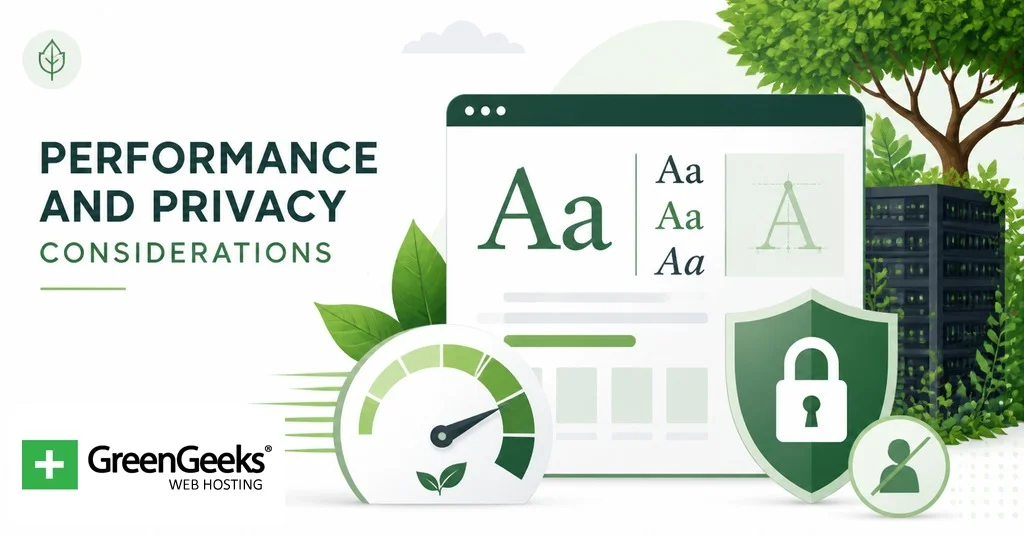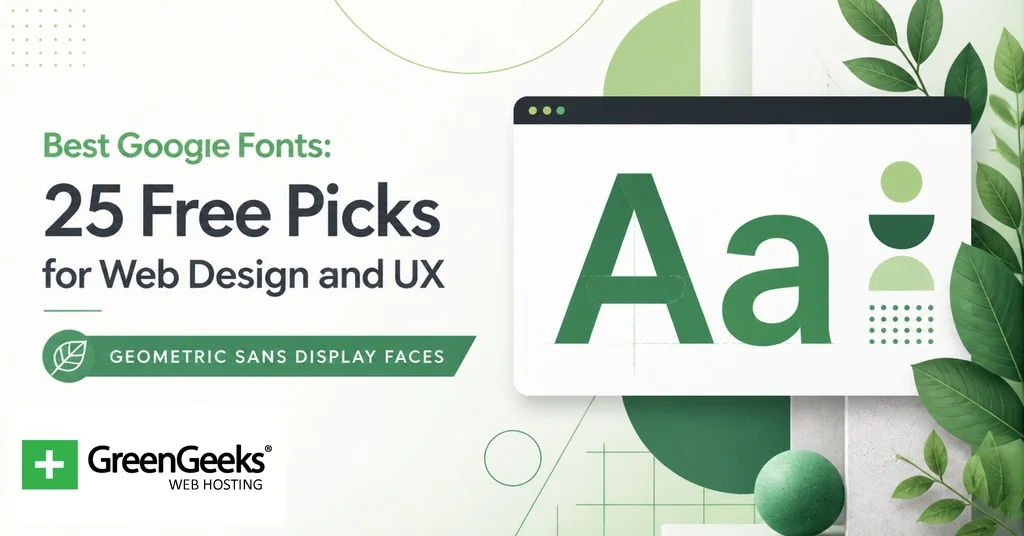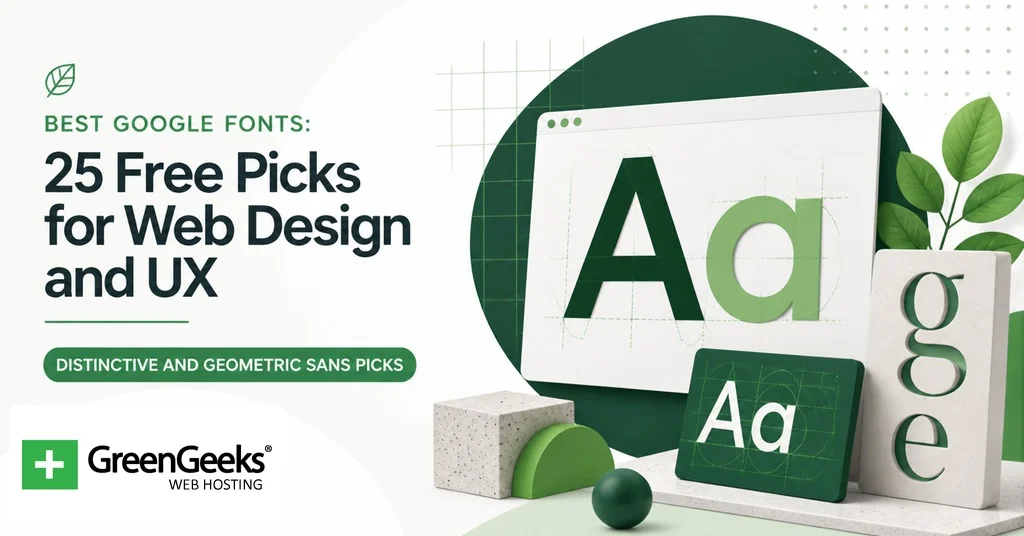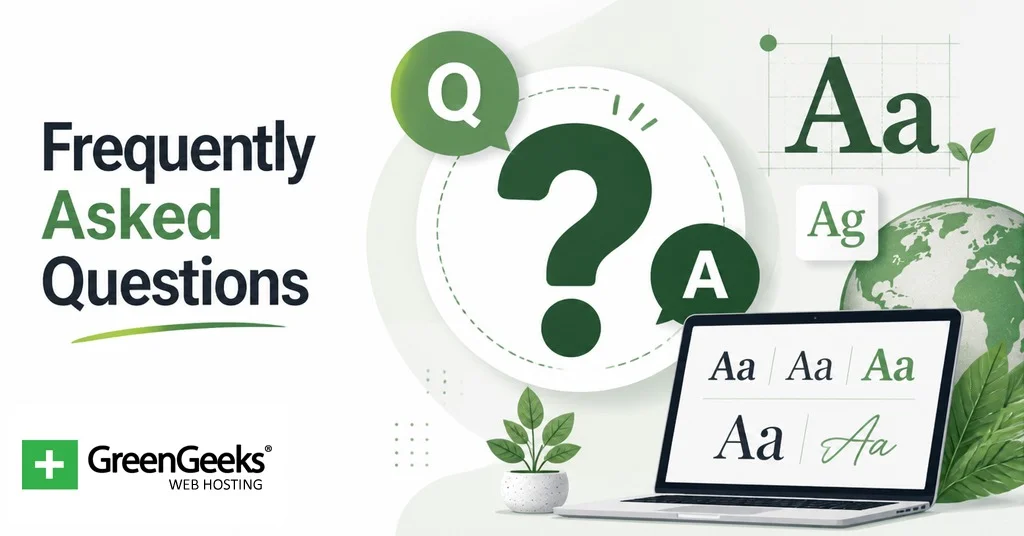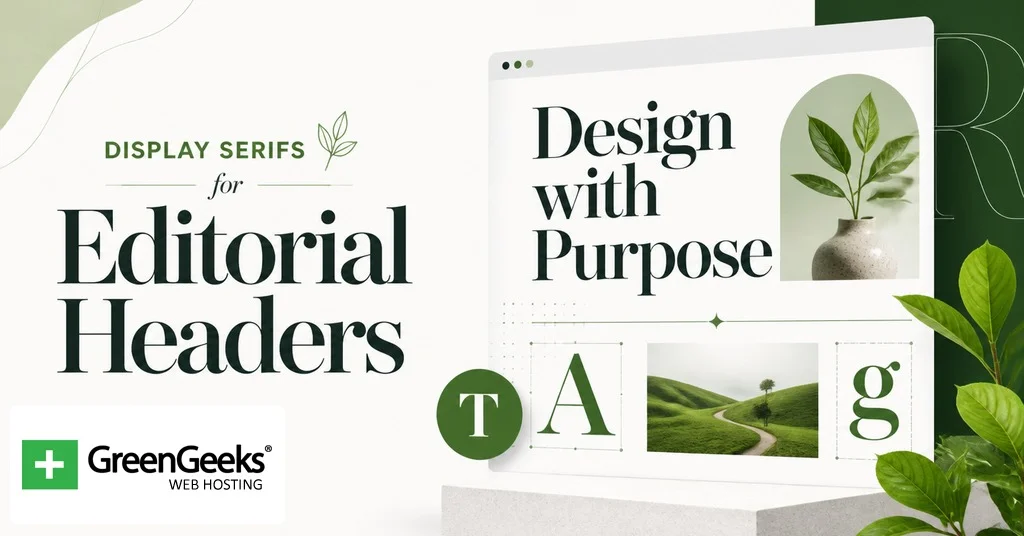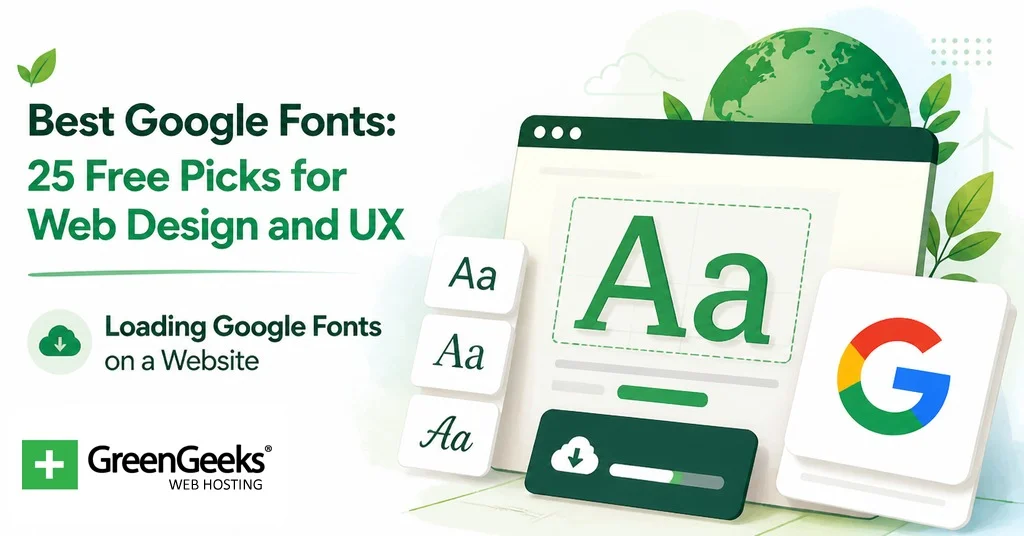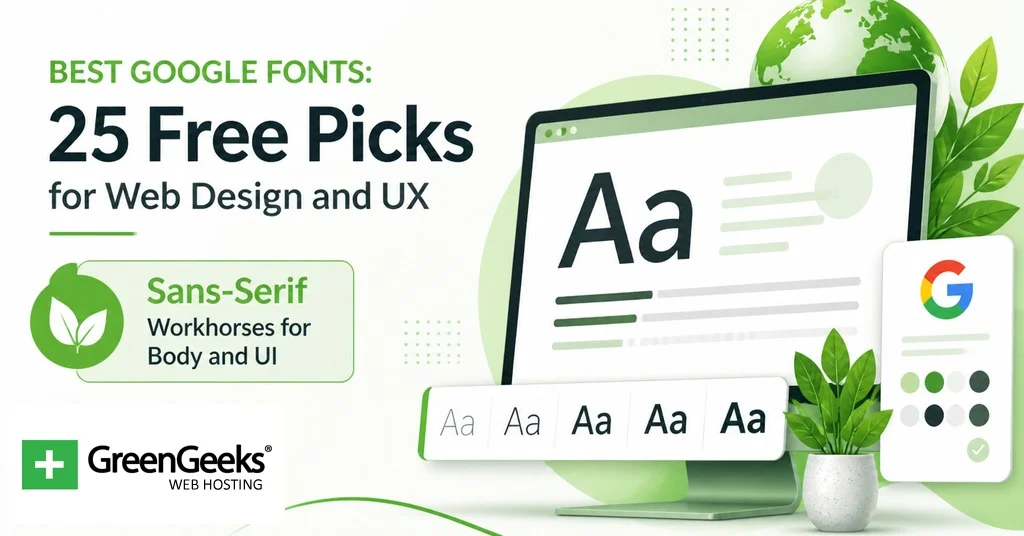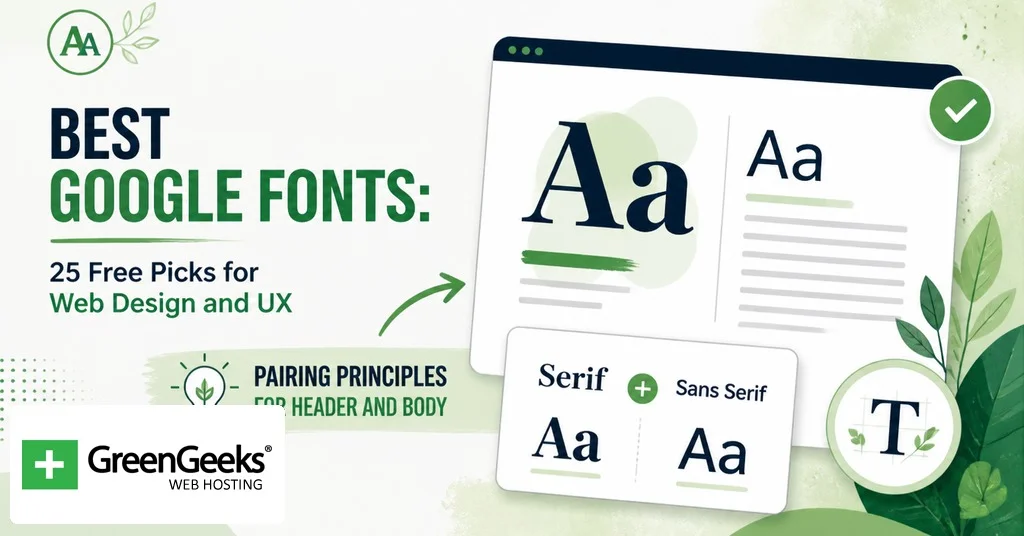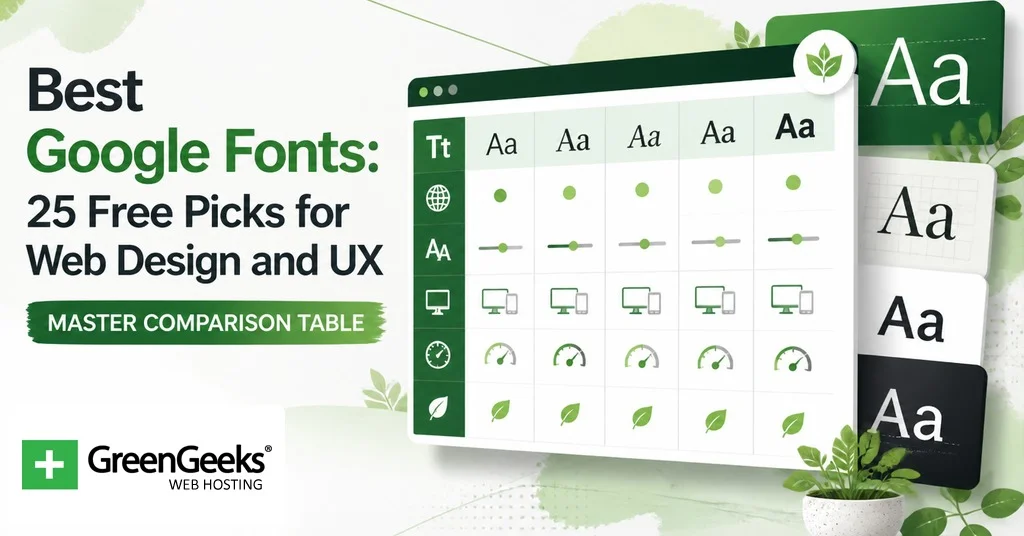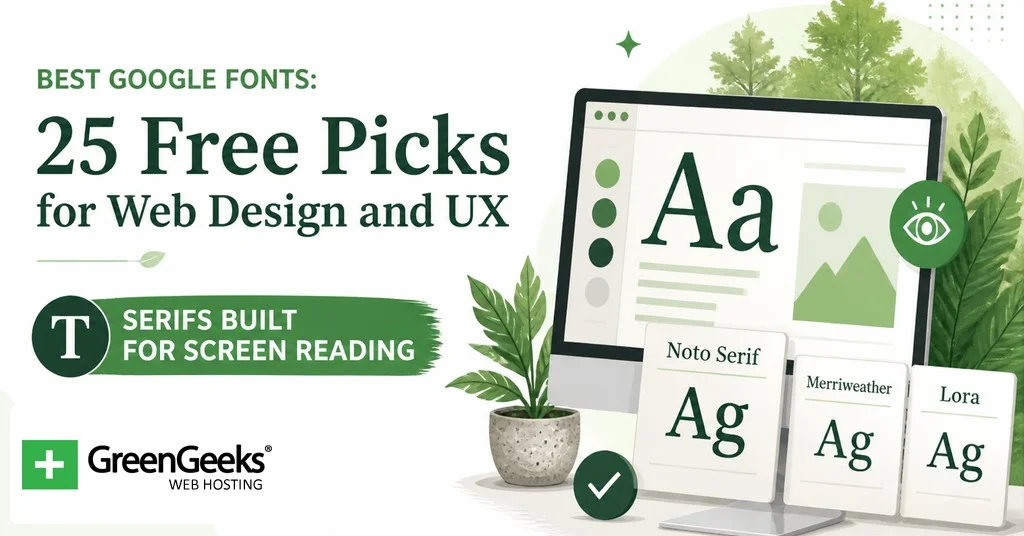
Inter, Roboto и Open Sans — самые используемые шрифты Google Fonts в открытом вебе, потому что они созданы для экранов, доступны во многих начертаниях и имеют открытую лицензию, разрешающую коммерческое встраивание. Приведённые ниже 25 вариантов расширяют это ядро в область шрифтов с засечками, брусковых, узких, моноширинных и адаптированных для доступности, чтобы дизайнер мог построить целый сайт — от геройских заголовков до сносок и примеров кода — не покидая каталога Google Fonts. Критериями являются данные об использовании, количество начертаний, оптический размер, языковое покрытие и то, как каждый шрифт выглядит в размерах для основного текста на базовой линии 16px.
Библиотека Google Fonts насчитывала 1 826 семейств в мае 2025 года и суммарно набрала более 50 триллионов просмотров на 50 миллионах веб-сайтов. Roboto лидирует по совокупным просмотрам — около 28 триллионов, а Inter за год, закончившийся в мае 2025 года, набрал 414 миллиардов просмотров, показав рост 57% год к году. Эти две цифры объясняют, почему большинство современных интерфейсов кажутся знакомыми. Приведённый ниже список рассматривает их как основу и добавляет ещё 23 шрифта, которые решают разные задачи: редакционные заголовки, доступность, код, брендинг.
Критерии отбора 25 шрифтов
Пять факторов сформировали шорт-лист. Первый — реальное использование. Шрифты, набравшие не менее миллиарда просмотров в год на Google Fonts, продвигались вверх, поскольку широкое распространение обычно коррелирует с качеством отображения в разных браузерах и операционных системах. Второй — количество начертаний. Шрифты, поставляемые с пятью и более начертаниями, дают дизайнерам пространство для иерархии без необходимости подключать второе семейство. Третий — оптический размер или экранная настройка. Inter, Roboto, Lexend и Atkinson Hyperlegible были созданы с явной целью отображения на экране с попиксельным рендерингом, что проявляется в том, как они выглядят при малом размере основного текста.
Четвёртым фактором стало языковое покрытие. Одной латиницы достаточно для большинства англоязычных сайтов, но расширенная латиница, кириллица и греческий важны для международного UX. PT Serif, Open Sans, EB Garamond и Atkinson Hyperlegible имеют хорошую поддержку нескольких письменностей. Пятым фактором стал размер файла после поднабора. Переменный шрифт в Google Fonts обычно занимает от 20 до 30 КБ после применения латинского поднабора, по сравнению с 400–800 КБ для эквивалентного набора статических файлов. Эта разница важна для показателей Largest Contentful Paint на мобильных устройствах.
Сводная сравнительная таблица
| Шрифт | Классификация | Начертания | Переменная ось | Лучше всего для |
| Inter | Нео-гротескный без засечек | 9 | Начертание, оптический размер | Основной текст, UI |
| Roboto | Нео-гротескный без засечек | 6 | Начертание, ширина (Flex) | Основной текст, UI |
| Open Sans | Гуманистический без засечек | 7 | Начертание | Основной текст, блог |
| Lato | Гуманистический без засечек | 9 | Только статические | Основной текст, бренд |
| Source Sans 3 | Гуманистический без засечек | 8 | Начертание | Основной текст, документация |
| Work Sans | Без засечек, адаптированный для экранов | 9 | Начертание | Основной текст, UI |
| Nunito | Закруглённый без засечек | 7 | Начертание | Дружественный интерфейс |
| DM Sans | Геометрический без засечек | 5 | Начертание, оптический размер | Мелкий текст |
| Montserrat | Геометрический без засечек | 9 | Начертание | Заголовки, бренд |
| Poppins | Геометрический без засечек | 9 | Только статические | Заголовки, бренд |
| Plus Jakarta Sans | Геометрический без засечек | 6 | Начертание | UI для SaaS |
| Manrope | Геометрический без засечек | 7 | Начертание | UI для SaaS |
| Bebas Neue | Узкий акцидентный | 1 | Только статические | Плакаты, геройский |
| Oswald | Узкий без засечек | 6 | Начертание | Новостные заголовки |
| Archivo | Без засечек, готический | 9 | Начертание, ширина | Редакционные |
| Raleway | Акцидентный без засечек | 9 | Начертание | Бренд, геройский |
| Space Grotesk | Пропорциональный без засечек | 5 | Начертание | Технологический бренд |
| Merriweather | Брусковый с засечками для основного текста | 4 | Только статические | Длинный основной текст |
| Lora | Каллиграфический с засечками | 4 | Начертание | Редакционный основной текст |
| PT Serif | Переходный с засечками | 2 | Только статические | Многоязычный основной текст |
| Playfair Display | Переходный акцидентный с засечками | 6 | Начертание | Редакционный заголовок |
| DM Serif Display | Высококонтрастный с засечками | 1 | Только статические | Геройский заголовок |
| EB Garamond | Старостильный с засечками | 5 | Начертание | Чтение длинных текстов |
| Roboto Slab | Брусковый с засечками | 9 | Начертание | Заголовки с привязкой к основному тексту |
| JetBrains Mono | Моноширинный | 8 | Начертание | Блоки кода |
Рабочие лошадки без засечек для основного текста и интерфейсов
Эти восемь шрифтов справляются с текстом абзацев, надписями навигации, полями форм и большинством интерфейсного текста. Их объединяют три качества, делающие их безопасным выбором по умолчанию: щедрая высота строчных, равномерный интервал и хинтинг для экранов с низким разрешением.
1. Inter
Созданный Расмусом Андерссоном и выпущенный в 2017 году, Inter — это нео-гротескный шрифт без засечек, оптимизированный для текста пользовательского интерфейса малых размеров. Переменный файл содержит как ось начертания (от 100 до 900), так и ось оптического размера с тремя мастер-дизайнами для 100, 400 и 900. Inter используется по умолчанию в нескольких крупных дизайн-системах и набрал 414 миллиардов просмотров в Google Fonts за год, закончившийся в мае 2025 года.
Чисто сочетается с самим собой. Один файл Inter с переменным начертанием покрывает заголовки, основной текст и UI без второго семейства.
2. Roboto
Кристиан Робертсон разработал Roboto для Android 4.0 в 2011 году. Он поставляется в начертаниях Thin, Light, Regular, Medium, Bold и Black, а также в наклонных версиях, а в 2022 году получил переменную версию Roboto Flex. Roboto имеет наибольшее количество просмотров за всё время в Google Fonts — около 28 триллионов. Его двойственный характер — геометрический скелет с гуманистическими кривыми — придаёт ему нейтральность, которая адаптируется к большинству продуктовых контекстов.
Пример сочетания: Roboto для основного текста, Roboto Slab для H1.
3. Open Sans
Open Sans — это гуманистический шрифт без засечек, созданный Стивом Мэттесоном по заказу Google в 2011 году. Набор символов охватывает 897 глифов для латиницы, греческого и кириллицы. Он имеет открытые формы букв и слегка вертикальный наклон, что обеспечивает читаемость длинных абзацев на маленьких экранах.
Примечание дизайнера: Мэттесон основал семейство на своём более раннем Droid Sans, созданном для Android в 2008 году.
4. Lato
Lato — это гуманистический шрифт без засечек, разработанный польским дизайнером шрифтов Лукашем Дзедичем и выпущенный в 2010 году. Он поставляется в 9 начертаниях с соответствующими курсивами. Шрифт имеет полузакруглённые формы букв, которые воспринимаются как тёплые, не теряя структурной строгости.
Обычное применение: корпоративные сайты и образовательные платформы, которым нужна более дружелюбная альтернатива Roboto.
5. Source Sans 3
Первый открытый шрифт Adobe, созданный Полом Хантом и выпущенный в 2012 году под названием Source Sans Pro. Source Sans 3 — это переименованный преемник с открытым исходным кодом. Шрифт поставляется в 8 начертаниях от ExtraLight до Black с соответствующими курсивами. Формы букв чистые и слегка узкие, поэтому текст набирается компактно, не кажется сжатым.
Используйте его там, где важна плотность документации, например в справках API или документации продуктов.
6. Work Sans
Адаптированный для экрана шрифт без засечек от Вэй Хуанга. Средние начертания (от 400 до 600) разработаны для размеров от примерно 14px до 48px. Более лёгкие и более жирные начертания имеют более декоративные начертания, поэтому дизайнеры могут переходить к акцидентному использованию, не меняя семейство.
7. Nunito
Вернон Адамс разработал Nunito как шрифт без засечек с закруглёнными концами. Закруглённые углы придают шрифту более мягкое ощущение по сравнению с Inter или Roboto. Nunito Sans, версия без закруглений, находится рядом с ним в каталоге Google Fonts для случаев, когда мягкие окончания кажутся слишком игривыми.
Сочетается с Lora для дружелюбной редакционной блог-системы.
8. DM Sans
DM Sans — это малоконтрастный геометрический шрифт без засечек от Colophon Foundry и Indian Type Foundry. Шрифт предназначен для малых размеров текста и поставляется с переменным файлом, имеющим ось начертания и ось оптического размера. Более плотный интервал хорошо читается в плотных панелях интерфейса и дашбордах.
Геометрические акцидентные шрифты без засечек
Эта группа склоняется к брендингу и заголовкам. Геометрия создаёт уверенное, современное впечатление. Использование для основного текста возможно, но открытые внутренние просветы могут казаться разреженными в длинных отрывках.
9. Montserrat
Хульета Улановски создала Montserrat в 2011 году, вдохновившись старыми плакатами и вывесками в районе Монтсеррат в Буэнос-Айресе. Семейство поставляется в 9 начертаниях. Геометрическая конструкция делает его частым выбором для геройских заголовков, фирменных знаков и слайдов презентаций.
Заметка из данных об использовании: Montserrat входит в тройку лучших шрифтов Google Fonts последние пять лет подряд.
10. Poppins
Геометрический гротеск от Indian Type Foundry, с указанием авторства Джонни Пинхорна и Нинада Кале. Poppins охватывает латиницу и деванагари, что редко встречается среди шрифтов Google Fonts. Поставляется в 9 начертаниях от Thin до Black. Буквенные формы почти монолинейны, что придает чистый, маркетинговый вид.
Пример сочетания: Poppins для заголовков, PT Serif для основного текста.
11. Plus Jakarta Sans
Спроектирован Гумпитой Рахаю из Tokotype. Выпущенный как SaaS-ориентированный геометрический гротеск, этот семейство набрало популярность в контексте стартапов и интерфейсов продуктов, где Inter кажется слишком избитым. Шесть начертаний с соответствующими курсивами.
12. Manrope
Manrope от Михаила Шаранды находится между геометрическим и гротескным. По духу ближе к коммерческим гарнитурам, таким как Circular, имеет слегка закрытые полуапроши, которые не позволяют геометрическим буквам выглядеть слишком открытыми при крупных размерах. Семь начертаний.
Узкие и жирные акцидентные гротески
Для плакатов, геройских секций и коротких блоков с сильным визуальным воздействием. Ни один из этих трех шрифтов не предназначен для набора абзацев.
13. Bebas Neue
Спроектированный Рёичи Цунекавой и добавленный в Google Fonts в 2018 году, Bebas Neue содержит только заглавные буквы и является узким. Версия в Google Fonts поставляется в единственном начертании. Bebas Neue Pro, продаваемая отдельно, добавляет строчные, но в большинстве редакторских применений Bebas Neue используется как полностью заглавный плакатный шрифт.
14. Oswald
Вернон Адамс переработал стиль Alternate Gothic для создания Oswald. Семейство поставляется в 6 начертаниях с полным набором строчных, что отличает его от Bebas Neue. Oswald подходит для газетных заголовков, шапок спортивных сайтов и любых макетов, требующих вертикального сжатия.
15. Archivo
Archivo вдохновлен американским готическим шрифтом XIX века. Релиз в Google Fonts поставляется как вариативный шрифт с осями ширины и начертания. Узкие начертания выглядят редакционно; обычные — как утилитарный гротеск для форм и плотных таблиц.
Выразительные и геометрические гротески
Два шрифта, решающие более узкие задачи, чем рабочие лошадки, но часто встречающиеся в современных бренд-системах.
16. Raleway
Изначально нарисован Мэттом Макинерни в 2010 году как единственное тонкое акцидентное начертание. Позже Пабло Импаллари и Родриго Фуэнсалида расширили семейство до 9 начертаний с курсивами. Raleway лучше всего смотрится при крупных размерах; тонкие и сверхлегкие начертания имеют фирменные лигатуры и слегка ар-дековую геометрию.
17. Space Grotesk
Флориан Карстен выпустил Space Grotesk в 2018 году как пропорциональный гротеск, производный от моноширинного Space Mono (2016) от Colophon Foundry. Семейство сохраняет своеобразные кривые и угловые срезы моноширинного оригинала, но оптимизирует межбуквенные расстояния для размеров, не связанных с отображением. Пять начертаний, без курсивов. Выглядит технологично, не переходя в научно-фантастический вид полностью геометрических шрифтов.
Антиквы для чтения с экрана
Три антиквы, которые успешно перешли из печати на экран. Каждая обладает большой высотой строчных знаков и слегка открытыми буквенными формами, которые хорошо смотрятся на экранах телефонов.
18. Merriweather
Sorkin Type разработал Merriweather как антикву для чтения с экрана. Шрифт имеет большую высоту строчных, слегка уплотненные формы и очень открытые апертуры. Это одна из самых часто цитируемых антикв для текста в блогах и публикациях. Четыре начертания от Light до Black.
19. Lora
Современная антиква с каллиграфическими корнями от Cyreal. По последним данным, Lora используется на более чем 1,5 миллионах сайтов. Она обладает достаточной теплотой для редакционного вида, не теряя регулярности, необходимой для абзацев. Четыре начертания с соответствующими курсивами.
20. PT Serif
PT Serif от ParaType поставляется с наборами латиницы, центральноевропейских языков и кириллицы. Семейство метрически совместимо с PT Sans, то есть оба семейства имеют одинаковую высоту строк и пропорции, поэтому они легко заменяют друг друга в системе. Два начертания с курсивами плюс два стиля для подписей.
Акцидентные антиквы для редакционных заголовков
Эти шрифты раскрываются при размере 32px и выше. Ни один из них не подходит для основного текста.
21. Playfair Display
Переходная антиква от Клауса Эггерса Соренсена. Дизайн отсылает к европейским шрифтам XVIII века и поставляется в 6 начертаниях. Высокий контраст штрихов и длинные верхние выносные элементы придают ему редакционный вид заголовка модного журнала. Обычно Playfair Display сочетают с чистым гуманистическим гротеском для основного текста.
22. DM Serif Display
Высококонтрастная переходная антиква, созданная для плакатов и геройских секций. Закругления деликатны, контраст штрихов сильный, а формы букв сохраняются только при больших размерах. В релизе Google Fonts одно начертание плюс курсив. Используйте при 40px или больше.
23. EB Garamond
Георг Майр-Даффнер нарисовал EB Garamond как бесплатное научное возрождение шрифтов Клода Гарамона XVI века. Пять начертаний с соответствующими курсивами. Семейство поддерживает латиницу, греческий и кириллицу. Дизайнеры обращаются к нему, когда контекст длинного чтения требует литературного регистра.
Брусковые и моноширинные шрифты
Два шрифта, дополняющих систему: брусковый для промежутка между гротеском и антиквой, и моноширинный для примеров кода.
24. Roboto Slab
Брусковая версия Roboto, выпущенная в марте 2013 года как шрифт по умолчанию для Google Keep. Семейство поставляется в 9 начертаниях от Thin до Black. Основное применение — компаньон для заголовков к основному тексту Roboto, где совпадающий скелет обеспечивает тесную визуальную связь.
25. JetBrains Mono
JetBrains выпустила JetBrains Mono в 2020 году под лицензией SIL Open Font License. Шрифт был нарисован для редакторов кода с максимальной высотой строчных для четкости при размерах 12–14px. Восемь начертаний с курсивами. Встроенный в любой документационный сайт или продукт, ориентированный на разработчиков, он придает блокам кода продуманный, инженерный вид.
Принципы сочетания заголовков и основного текста
Системы из двух шрифтов обычно побеждают. В большинстве продакшн-сайтов используется один акцидентный шрифт для H1 и H2 и один рабочий для основного текста, навигации и интерфейса. Иногда добавляют третий для кода или цифр, но после трех страница начинает выглядеть несогласованно.
Сильные сочетания работают на контрасте. Сочетайте высококонтрастную антикву с низкоконтрастным гротеском. Сочетайте геометрический гротеск с гуманистической антиквой. Сочетайте узкий акцидентный шрифт с широким рабочим. Сочетания в одном настроении обычно проваливаются, потому что страница теряет иерархию. Три надежных сочетания из списка выше: Playfair Display с Source Sans 3, Montserrat с Merriweather и Inter с самим собой в разных начертаниях.
Совпадение высоты строчных — второе правило. Если у шрифта для основного текста большая высота строчных, а у заголовочного — маленькая, то при одинаковом размере в пикселях основной текст будет выглядеть крупнее заголовков. PT Serif и PT Sans были спроектированы вместе специально для решения этой проблемы. Inter и Roboto Slab обладают достаточно схожей пропорциональной ДНК, чтобы вести себя аналогично. При сочетании шрифтов разных найденрий ставьте оба рядом в нужных размерах и проверяйте оптический баланс перед запуском.
Третье правило, которое стоит соблюдать, — ограничение начертаний. Используйте не более трех начертаний на шрифт на одной странице. Типичная настройка: Regular для основного текста, Medium для акцентов и Bold для заголовков. Добавление дополнительных начертаний не повышает ясность, а размывает иерархию.
Загрузка Google Fonts на сайте
Есть два способа загрузить шрифт Google с CDN Google, плюс третий — самостоятельный хостинг тех же файлов. У каждого есть свои компромиссы по производительности, конфиденциальности и кэшированию. Шаги по реализации ниже охватывают все три.
Выберите шрифт и начертания на fonts.google.com и скопируйте сгенерированный тег link.
Вставьте тег link в head HTML перед основным файлом стилей.
Укажите шрифт в CSS с помощью объявления font-family.
Добавьте font-display: swap в блок @font-face (или положитесь на значение по умолчанию Google, которое уже включает swap).
Для самостоятельного хостинга скачайте файлы шрифтов через кнопку загрузки Google Fonts, поместите их в папку /fonts и вручную напишите блок @font-face.
Добавьте тег link с rel=preload для наиболее используемого файла шрифта, чтобы устранить смещение макета при первой отрисовке.
Подход с тегом link выглядит так:
<link rel="preconnect" href="https://fonts.googleapis.com"> <link rel="preconnect" href="https://fonts.gstatic.com" crossorigin> <link href="https://fonts.googleapis.com/css2?family=Inter:wght@400;600;700&display=swap" rel="stylesheet">
Альтернатива CSS @import загружает те же файлы, но блокирует рендеринг до разрешения импорта:
@import url('https://fonts.googleapis.com/css2?family=Inter:wght@400;600;700&display=swap'); body { font-family: 'Inter', system-ui, sans-serif; }
Самостоятельно размещенный блок выглядит так и полностью исключает сторонний запрос:
@font-face { font-family: 'Inter'; src: url('/fonts/inter-variable.woff2') format('woff2-variations'); font-weight: 100 900; font-display: swap; }
Сочетайте самостоятельно размещенный блок с тегом preload в заголовке документа для соответствующего файла, и страница будет отрисована при первой отрисовке с веб-шрифтом без мигания запасного варианта.
Вопросы производительности и конфиденциальности
Переменный шрифт заменяет от 4 до 9 статических файлов одним. После латинской подрезки типичный переменный шрифт из Google Fonts весит от 20 до 30 КБ, тогда как эквивалентный набор статических файлов — от 400 до 800 КБ. Такое сокращение полезной нагрузки напрямую влияет на Largest Contentful Paint в мобильных сетях. Для сайта, которому нужна только латиница, применение текстового URL-параметра в запросе к Google Fonts или запуск pyftsubset на самостоятельно размещённом файле уменьшает размер файла ещё на 70–90 процентов.
Свойство CSS font-display управляет тем, что происходит, пока файл загружается. Установка font-display: swap немедленно отображает запасной шрифт и заменяет его веб-шрифтом, когда тот готов, что обменивает короткую вспышку нестилизованного текста (FOUT) на более быстрый First Contentful Paint. Установка font-display: optional даёт браузеру около 100 миллисекунд на загрузку шрифта; если он не успевает, запасной шрифт фиксируется на всю загрузку страницы. Комбинация предзагрузки, optional и самостоятельно размещённого файла устраняет как FOIT (вспышку невидимого текста), так и FOUT на большинстве кэшированных посещений.
Проблема конфиденциальности специфична для CDN Google. В январе 2022 года Мюнхенский земельный суд постановил, что загрузка шрифтов Google с fonts.googleapis.com без согласия передаёт IP-адрес пользователя в США и нарушает GDPR. Истцу была присуждена компенсация в размере 100 евро, и суд указал на более высокие штрафы за повторные нарушения. Множество судов ЕС последовали этому прецеденту. Самостоятельное размещение файлов шрифтов решает проблему, поскольку при загрузке страницы не выполняется внешний запрос. Лицензия Open Font License явно разрешает такое распространение. Для сайта со значительным европейским трафиком самостоятельное размещение является более безопасным выбором по умолчанию в 2026 году.
Практическая настройка объединяет три шага: загрузите переменный шрифт из Google Fonts, выполните латинскую подрезку с помощью pyftsubset и разместите файл на том же домене, что и сайт, с длинным заголовком Cache-Control и тегом предзагрузки. Такая конфигурация обеспечивает полезную нагрузку менее 30 КБ, отсутствие сторонних запросов и отсутствие FOIT на кэшированных посещениях.
Часто задаваемые вопросы
Какой шрифт Google лучше всего подходит для веб-сайтов?
Inter, Roboto и Open Sans возглавляют списки использования и рекомендаций для общих веб-задач. Они были разработаны для экранов, поставляются во многих начертаниях и хорошо читаются в размерах основного текста от 16 до 18 пикселей. Inter показывает самый сильный текущий рост в Google Fonts, в то время как Roboto занимает наибольшую совокупную долю — примерно 28 триллионов просмотров за всё время.
Какой шрифт Google самый читаемый?
Inter и Open Sans чаще всего упоминаются как наиболее читаемые для основного текста благодаря высокой высоте строчных букв, открытым формам и равномерным интервалам. Для читателей с ослабленным зрением или трудностями при чтении Atkinson Hyperlegible (выпущен Институтом Брайля в 2021 году) и Lexend (разработан для улучшения навыков чтения) являются самыми сильными вариантами с точки зрения доступности в каталоге Google Fonts.
Можно ли использовать Google Fonts в 2026 году?
В целом да, но загрузка шрифтов с CDN Google без предварительного согласия была признана нарушением GDPR Мюнхенским земельным судом и рядом последующих дел. Самостоятельное размещение тех же файлов шрифтов устраняет этот риск, сохраняя преимущества лицензии Open Font License, и обычно улучшает производительность за счёт более строгого контроля кэширования.
Что такое переменный шрифт?
Переменный шрифт хранит несколько начертаний, ширин или оптических размеров в одном файле вдоль определённых осей. Один переменный шрифт может заменить от 4 до 9 статических файлов. После латинской подрезки типичный переменный файл весит от 20 до 30 КБ, тогда как эквивалентный статический набор — от 400 до 800 КБ. Inter, Roboto Flex и Plus Jakarta Sans поставляются как переменные шрифты в Google Fonts.
Как добавить шрифты Google на мой сайт?
Скопируйте сгенерированный тег link с fonts.google.com в раздел head вашего HTML, затем укажите шрифт в CSS с помощью объявления font-family. Тег link предпочтительнее @import, поскольку он не блокирует загрузку. Для лучшей конфиденциальности и производительности скачайте файлы и разместите их самостоятельно с помощью блока @font-face, включающего font-display: swap и тег link с rel=preload для основного файла.